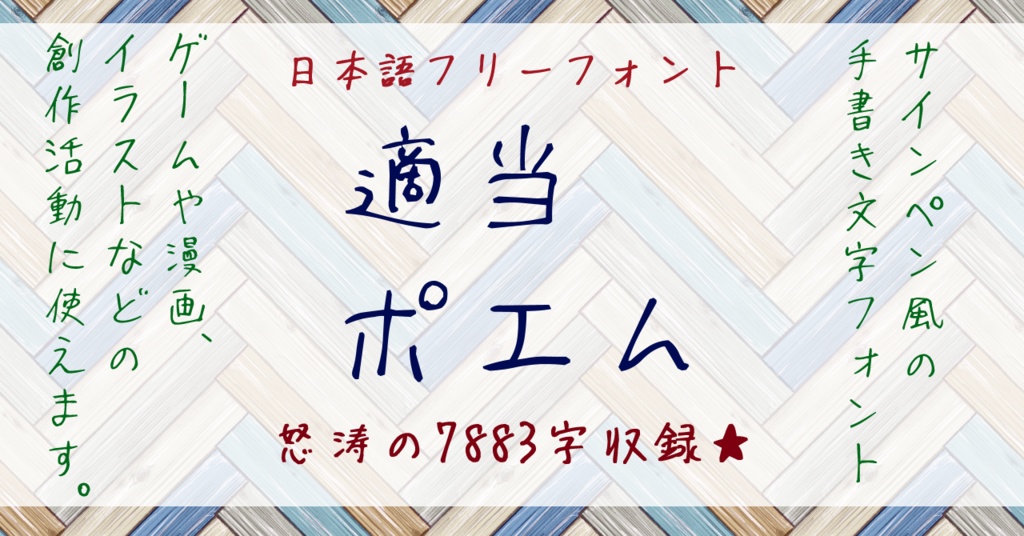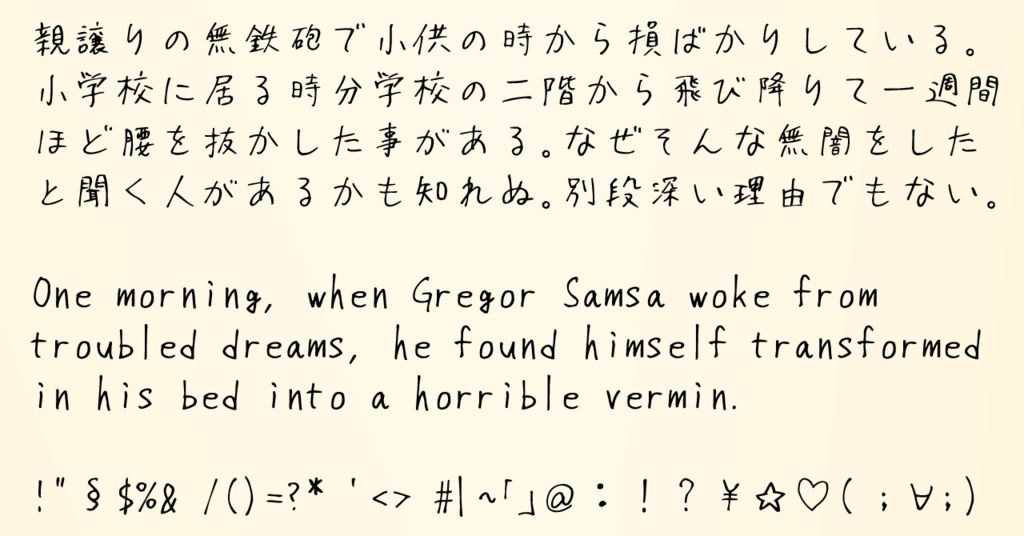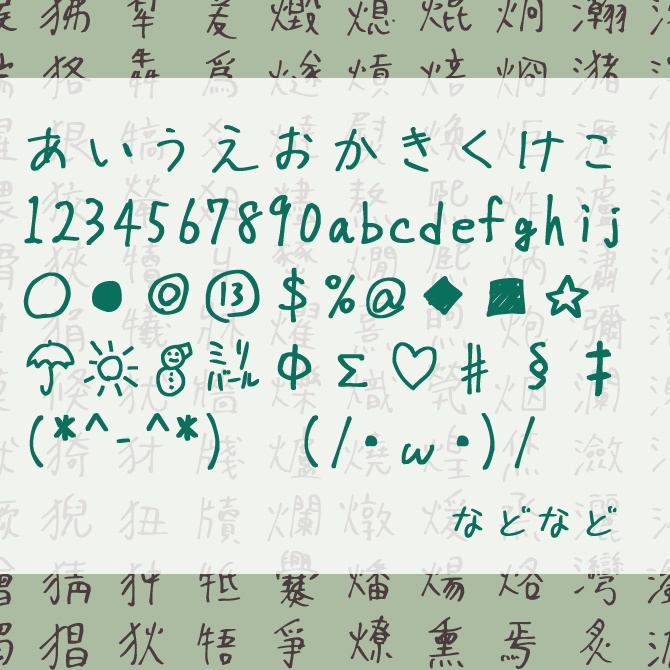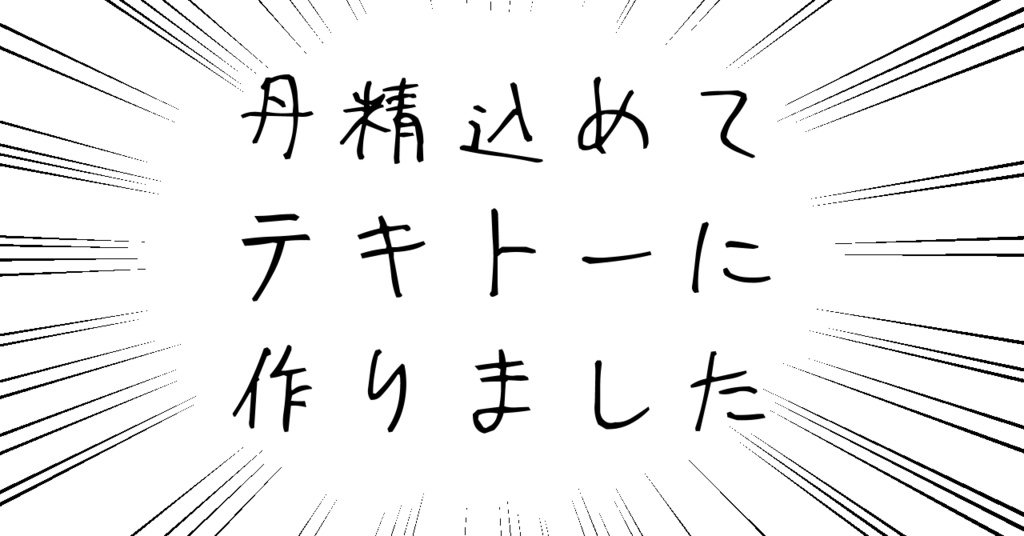
这是一个适合手写的日语字体。 包含平假名、片假名、第一水平汉字、第二水平汉字、其他汉字、英文数字和符号等共7883个字符。
可以在游戏、插图、动画、印刷物等各种用途中使用。 字符的大小和书写风格有所不同。
“適当ポエムTekitouPoem”是一款书写很新颖的字体,字体大方,适合各种设计作品使用!欢迎下载!